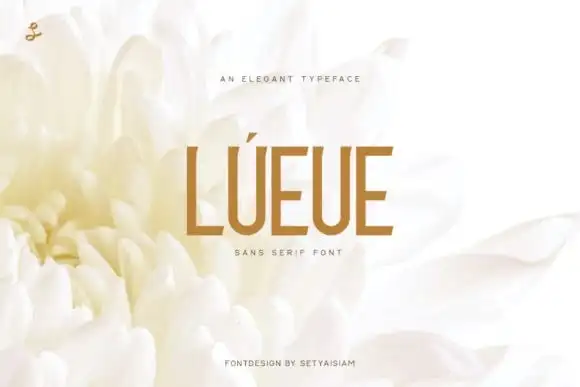
A Lueue Sans Serif é uma fonte de estilo chamado que se destaca por sua simplicidade e facilidade de leitura, tornando-a ideal para uma variedade de projetos visuais. Ela transmite um conforto casual enquanto ainda mantém a elegância necessária para uma apresentação impecável em qualquer tamanho. Com seu design cuidadosamente pensado, é perfeita tanto para aplicações pequenas e detalhadas quanto para materiais impressos com grande escala ou para sites e redes sociais. Seu designer na 99designs, setyaisiam, criou uma fonte que combina bem com um amplo espectro de projetos, permitindo-lhe explorar novas ideias criativas enquanto evidencia sua habilidade ao criar design impactante. A Lueue Sans Serif é a escolha perfeita para qualquer designer gráfico, se você está buscando uma fonte que atenda tanto à elegância quanto à praticidade. Seja para criar um texto dinâmico em suas redes sociais ou um layout sofisticado para seu site de moda, esta fonte oferece o equilíbrio perfeito entre design e legibilidade. Não hesite em adicioná-la a sua coleção de recursos gráficos e veja como ela pode destacar seus projetos!